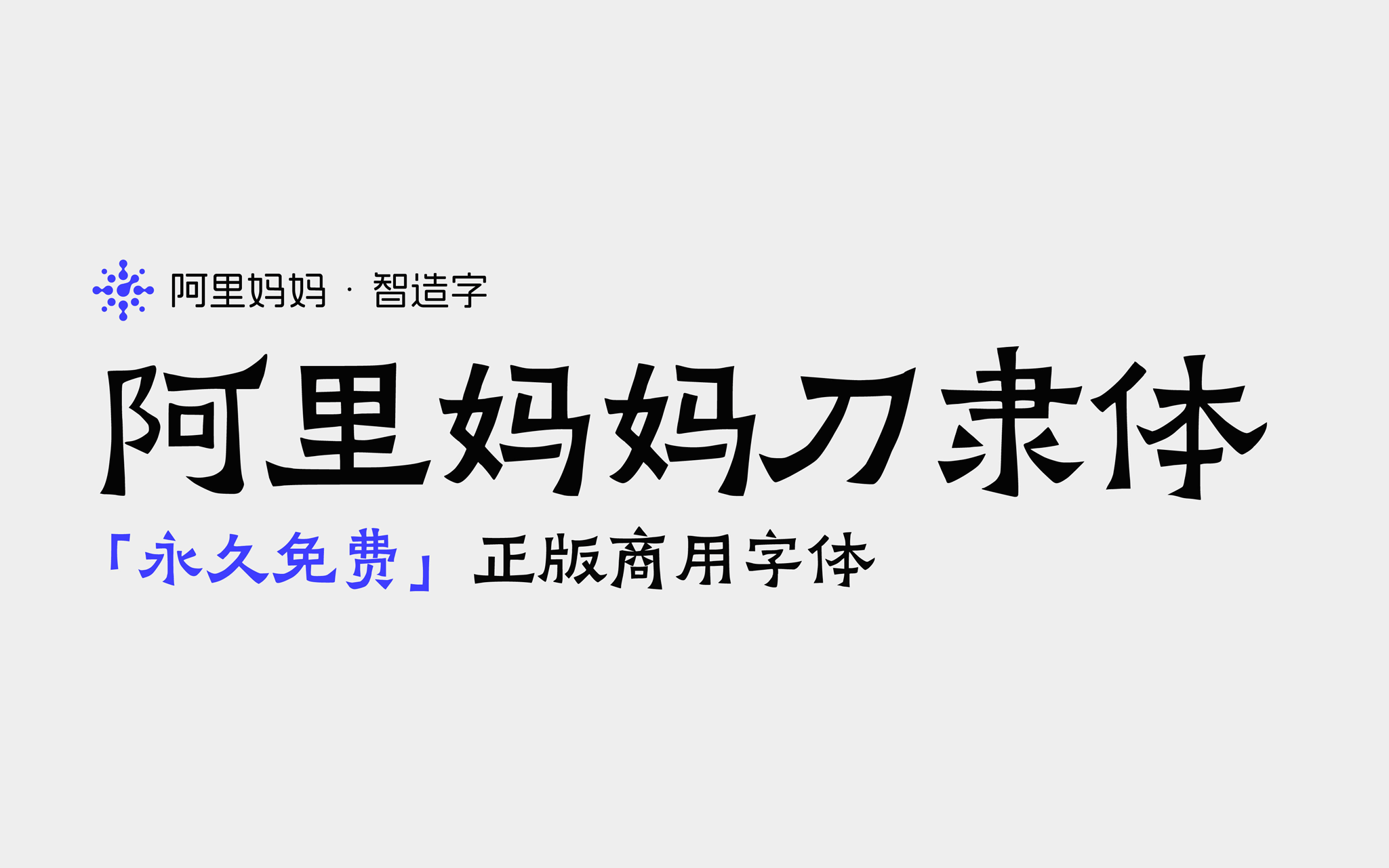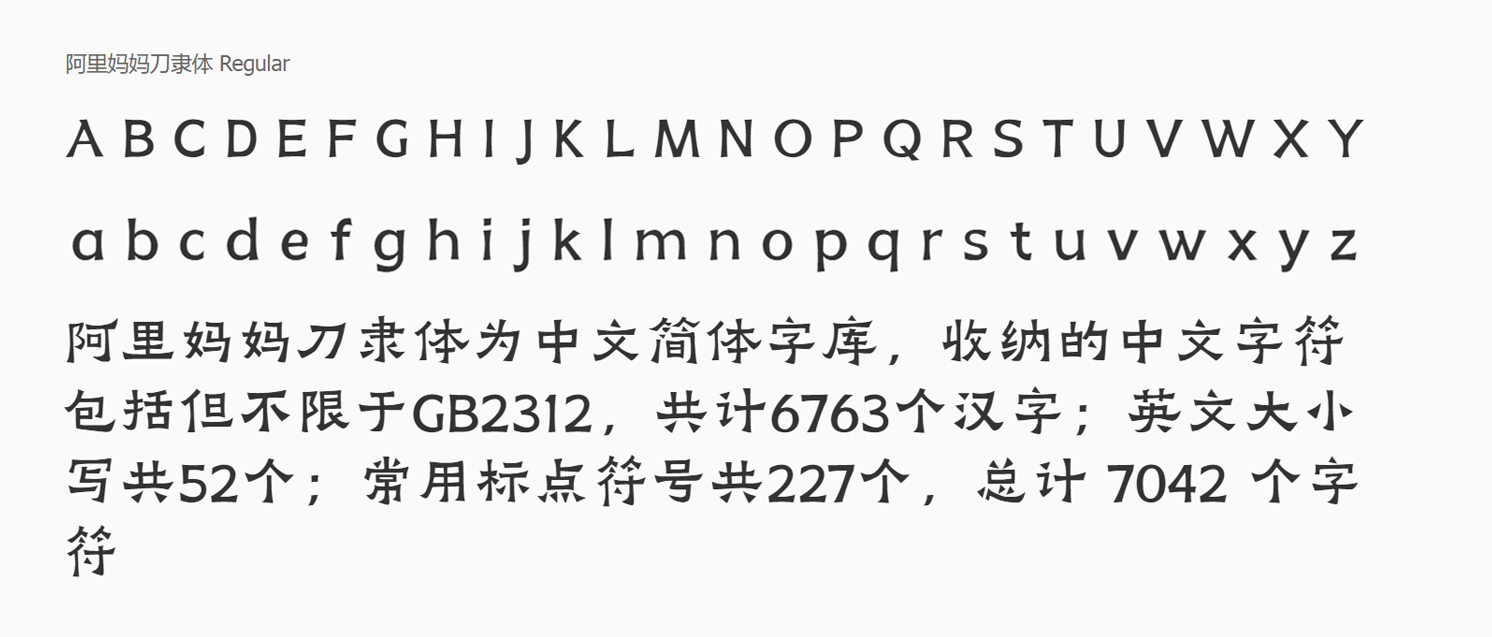
阿里妈妈刀隶体是由阿里妈妈·智造字通过机器学习了爨宝子碑的精髓,强调了三角点折弯与横画两端“雁尾”之方强,外露锋芒,耀其精神,介于隶楷之间,保持着浓重的隶书方笔意味,给人以坚实、朴茂、稚拙、倔犟之感,打破常规常态的匀称均衡,结字极为大胆,大小常常出人意料,看似失度,实则深得艺理,险中求正,静中寓动,动中求静。
阿里妈妈刀隶体为中文简体字库,收纳的中文字符共计6763个(包括但不限于GB2312);英文大小写共52个;常用标点符号共227个,总计 7042 个字符。
阿里妈妈刀隶体(AlimamaDaoLiTi)字形预览